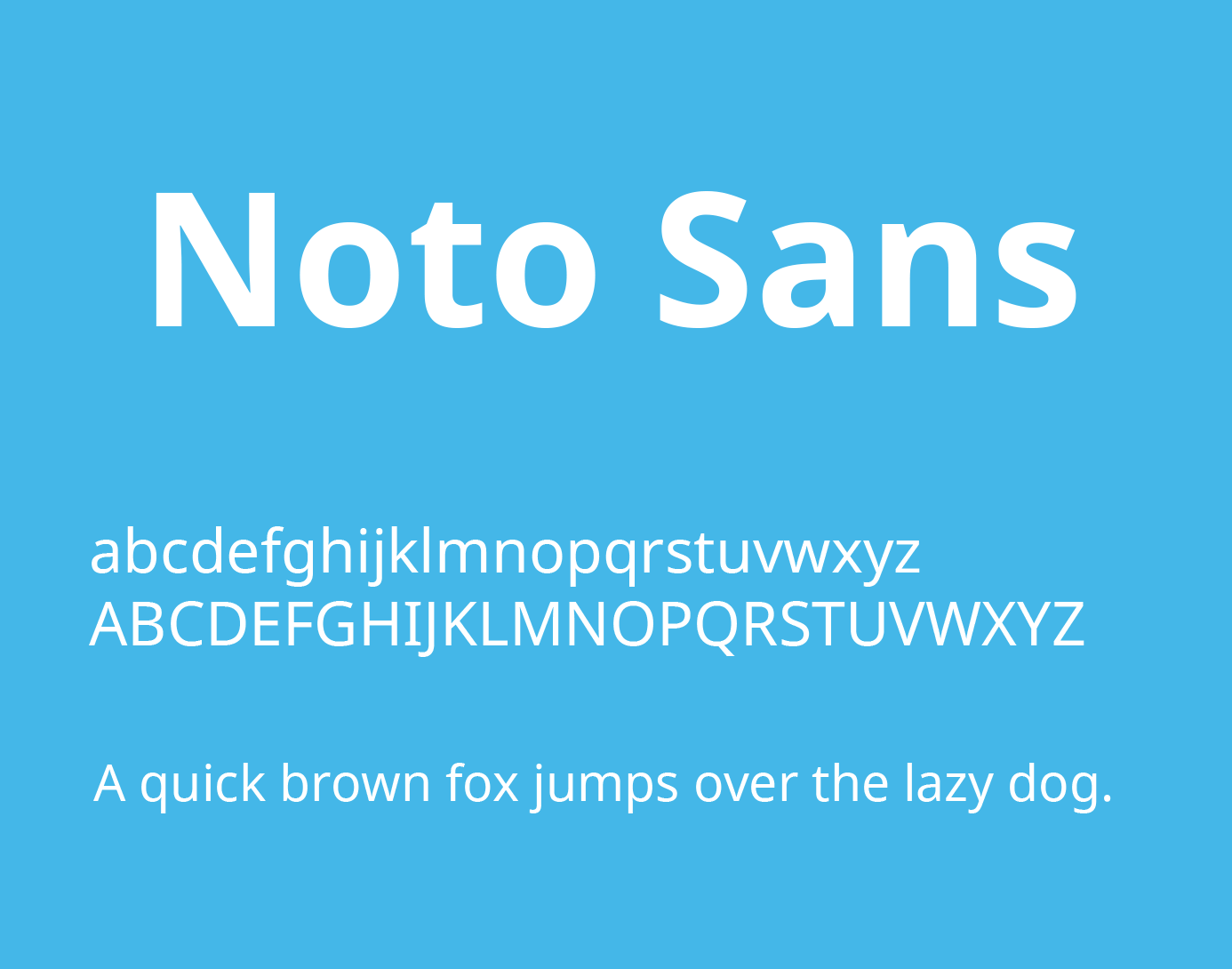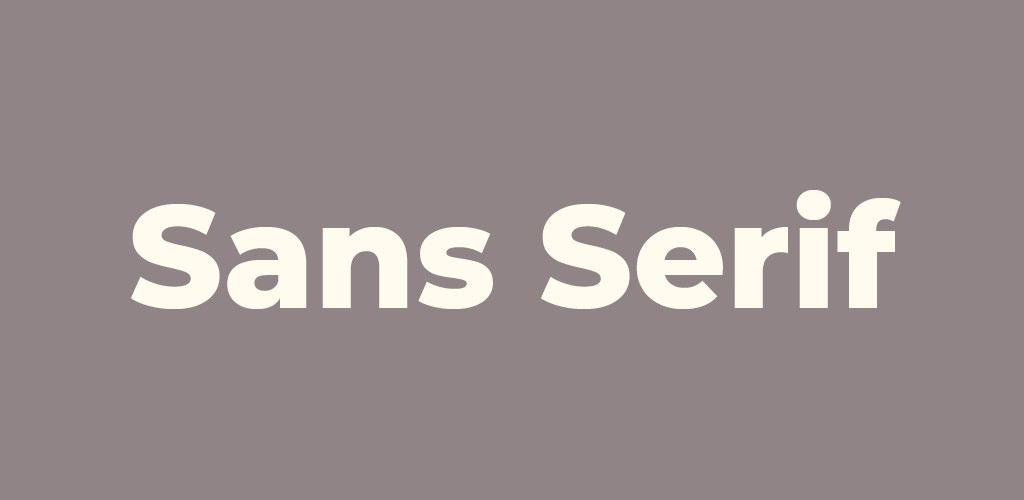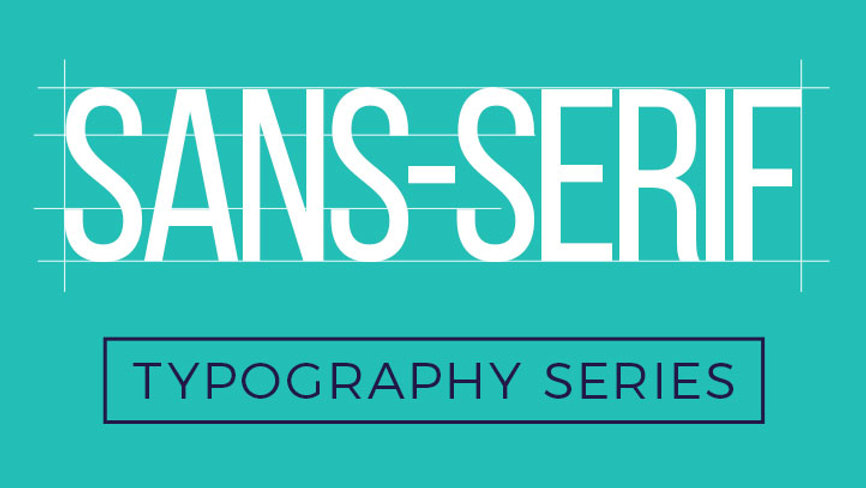
Tải font Sans-serif là bước chuẩn bị không thể thiếu của các designer khi bắt đầu dự án thiết kế bao bì, logo hoặc giao diện website hiện đại. Sans-serif (phông chữ không chân) nổi tiếng với cấu trúc tối giản, dứt khoát, mang lại cảm giác minh bạch, chuyên nghiệp và đặc biệt dễ đọc ở mọi kích thước. Doozypack.vn tổng hợp link download font sans serif Việt hóa trọn bộ, giúp bạn sở hữu những bộ phông chữ chỉn chu nhất mà không lo gặp lỗi dấu tiếng Việt khi đưa file vào sản xuất thực tế.
Font Sans-serif là gì và tại sao nên sử dụng trong thiết kế bao bì?
Thuật ngữ “Sans-serif” có nguồn gốc từ tiếng Pháp, trong đó “Sans” nghĩa là không có. Đây là nhóm các phông chữ không có các nét gạch ngang (serif) ở phần chân và đầu của mỗi ký tự.
Mẫu chữ sans serif hiện đại
Đặc điểm không chân hiện đại và tối giản
Đặc trưng lớn nhất của dòng font này là các đường nét dứt khoát, độ dày nét thường đồng đều, tạo nên hình khối chữ gọn gàng và thoáng đãng. Phong cách này giúp bản thiết kế thoát khỏi vẻ khô khan, thay vào đó là sự năng động và tân thời, cực kỳ phù hợp với xu hướng Minimalism (tối giản) đang thống trị ngành đồ họa thế giới.
Ưu điểm về độ hiển thị và trải nghiệm đọc
Nhờ cấu trúc sạch sẽ, các font sans-serif duy trì được độ sắc nét đáng kinh ngạc ngay cả khi hiển thị ở độ phân giải thấp hoặc in ở kích thước cực nhỏ trên tem nhãn dán sản phẩm. Mắt người có xu hướng nhận diện mặt chữ không chân nhanh hơn, giúp khách hàng dễ dàng nắm bắt thông tin quan trọng trên bao bì chỉ trong vài giây quan sát.
Kiểu chữ tối giản dễ đọc
Doozypack.vn cung cấp hệ thư viện đa dạng, từ các dòng Sans-serif hình học chuẩn xác đến các bộ Humanist Sans-serif thân thiện, tương thích hoàn hảo cho in ấn chuyên nghiệp.
Tên Font / Nhóm Font Đặc điểm thị giác Ứng dụng đề xuất tại Doozypack.vn
Geometric Sans (Montserrat, Futura) Hình khối chuẩn xác, hiện đại Thiết kế logo startup, bao bì công nghệ, linh kiện điện tử.
Humanist Sans (Open Sans, Myriad Pro) Mềm mại, dễ đọc, trung tính Dùng cho bảng thành phần, hướng dẫn sử dụng, nội dung chi tiết.
MS Sans Serif (Microsoft System) Chân phương, cổ điển Tải font ms sans serif cho các văn bản hành chính hoặc nhãn mã vạch.
03 Ứng dụng của font Sans-serif trong in ấn thực tế tại Doozypack.vn
Vẻ đẹp minh bạch của các dòng phông chữ không chân mang lại hiệu quả thị giác đặc biệt trên các ấn phẩm thực tế:
• Hộp dược phẩm & Mỹ phẩm: Sự sạch sẽ của font Sans-serif gợi cảm giác an toàn, minh bạch về thành phần và uy tín của thương hiệu dược mỹ phẩm.
• Túi giấy doanh nghiệp: Tên công ty in bằng Sans-serif Bold trên túi giấy Ivory cán màng mờ tạo phong thái vững chãi, hiện đại và đẳng cấp.
• Tem nhãn dán thông số: Cấu trúc rõ ràng giúp các khối văn bản nhỏ (Ingredients, Instructions) trên tem decal vẫn cực kỳ rõ nét, không bị bết mực khi in hàng loạt.
tai-font-sans-serif-5
Thiết kế typography gọn gàng
Lưu ý kỹ thuật khi in ấn font không chân kích thước nhỏ
Sản xuất bao bì sử dụng phông chữ Sans-serif đòi hỏi designer cần lưu ý một số vấn đề kỹ thuật tại xưởng in chuyên nghiệp:
• Kiểm soát hiện tượng Dot Gain: Đối với các phông chữ không chân nét mảnh (Light/Thin), mực in có thể bị lan nhẹ làm nét chữ trông mập hơn thiết kế. Hãy giữ size chữ tối thiểu từ 5.5pt – 6pt trên giấy Ivory phẳng mịn.
• Hệ màu CMYK cho văn bản: Luôn thiết kế trên hệ màu CMYK. Đặc biệt với màu đen cho văn bản nhỏ, hãy sử dụng thông số K=100 để chữ sắc nét nhất, tránh hiện tượng nhòe màu (lé bản kẽm).
5. In font Sans-serif trên túi giấy Kraft màu nâu có bị mờ không?
Nếu bạn sử dụng màu in đậm và size chữ từ 7pt trở lên, phông chữ Sans-serif hiển thị rất rõ ràng trên giấy Kraft, tạo nên phong cách Vintage cực kỳ thu hút.